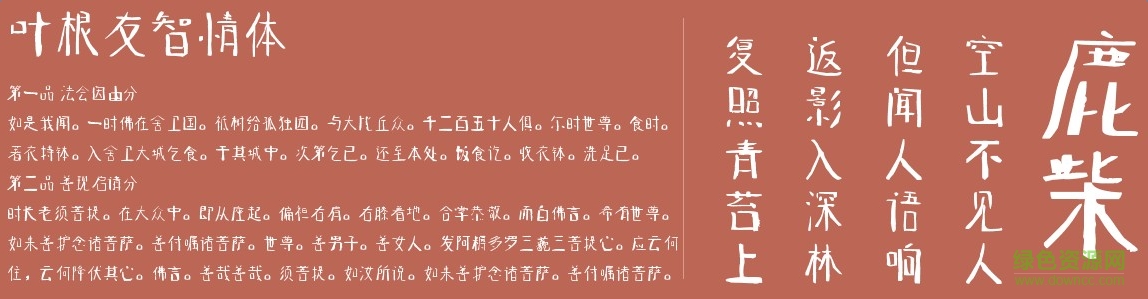
葉根友智情字體是一款由知名書(shū)法家葉根友創(chuàng)造的字體,適用于廣告設(shè)計(jì)、藝術(shù)、海報(bào)設(shè)計(jì)等方面,有需要的朋友們不要錯(cuò)過(guò)了。小編為大家提供免費(fèi)下載地址。歡迎大家來(lái)綠色資源網(wǎng)踴躍下載哦!
葉根友智情字體,2016年度最新發(fā)布的字體,是一款柔性的字體,非常靈動(dòng)有趣,活潑,海報(bào)設(shè)計(jì)、藝術(shù)方面可以使用。
葉根友智情字體,用途廣泛,是葉根友先生的手寫(xiě)字體,字體非常靈巧生動(dòng),適用于藝術(shù)設(shè)計(jì)等方面。各位字體收藏者可以來(lái)看看。